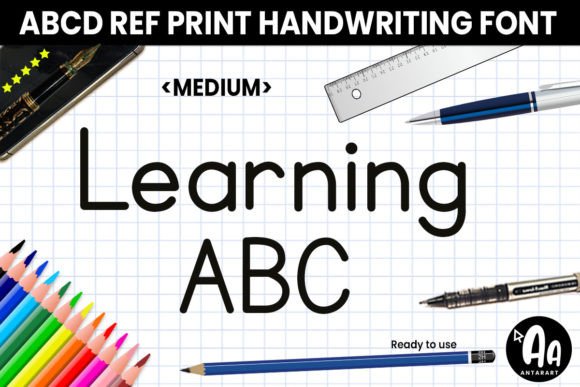
Abcd Ref Medium
Việc tìm kiếm các thành phần thiết kế phù hợp có thể là một thách thức, nhưng Abcd Ref Medium cung cấp một bộ sưu tập đặc biệt giúp nâng tầm công việc của bạn ngay lập tức.
Cho dù bạn đang tạo sản phẩm POD (In theo yêu cầu), thiệp mời đám cưới hay đồ họa mạng xã hội, Abcd Ref Medium đều là một sự lựa chọn lý tưởng.